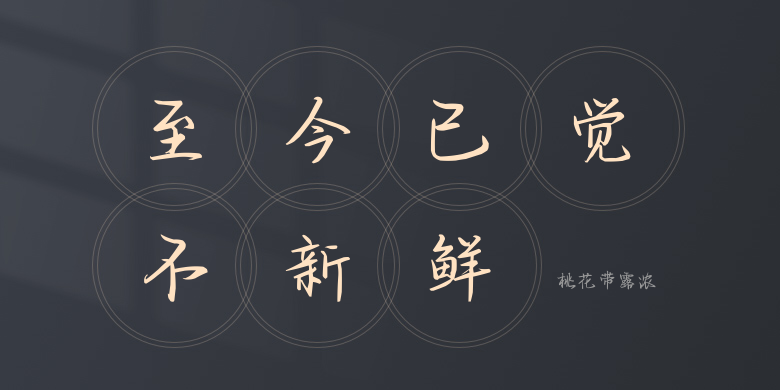
桃花带露浓
桃花带露浓,这款字体结构工整、笔画清晰,兼顾美观与易读性,适用于标题、正文、海报、包装、LOGO 等多种场景。字形优雅稳定,风格百搭耐看,适配日常排版与创意设计,让文字呈现更舒适、更具质感。桃花带露浓一笔一画,皆是细节,以均衡的比例、流畅的线条打造舒适视觉体验,字形端正大气,风格简约现代。无论是商业设计、品牌宣传还是日常排版,都能轻松驾驭,让文字更有格调与力量。桃花带露浓字体下载。